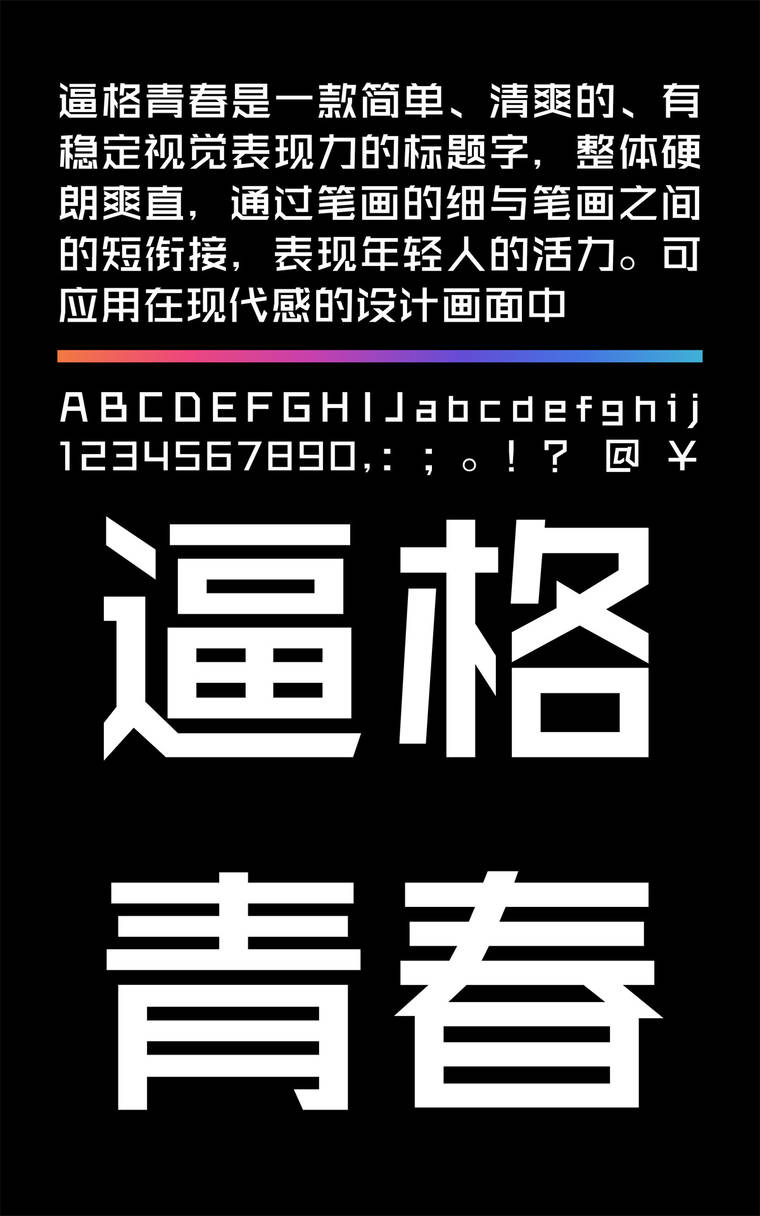
锐字逼格青春体简2.0 粗黑
锐字逼格青春体简2.0 粗黑字体介绍
锐字逼格青春体简2.0 粗黑,是锐字系列品牌字库旗下的一款字体。锐字潮牌字库拥有本字体独家版权,并提供锐字逼格青春体简2.0 粗黑的官方免费下载服务。
字体特征:逼格青春体是一款简单、清爽的、有稳定视觉表现力的标题字,整体硬朗爽直,通过笔画的细与笔画之间的短衔接,表现年轻人的活力。可应用在现代感的设计画面中。